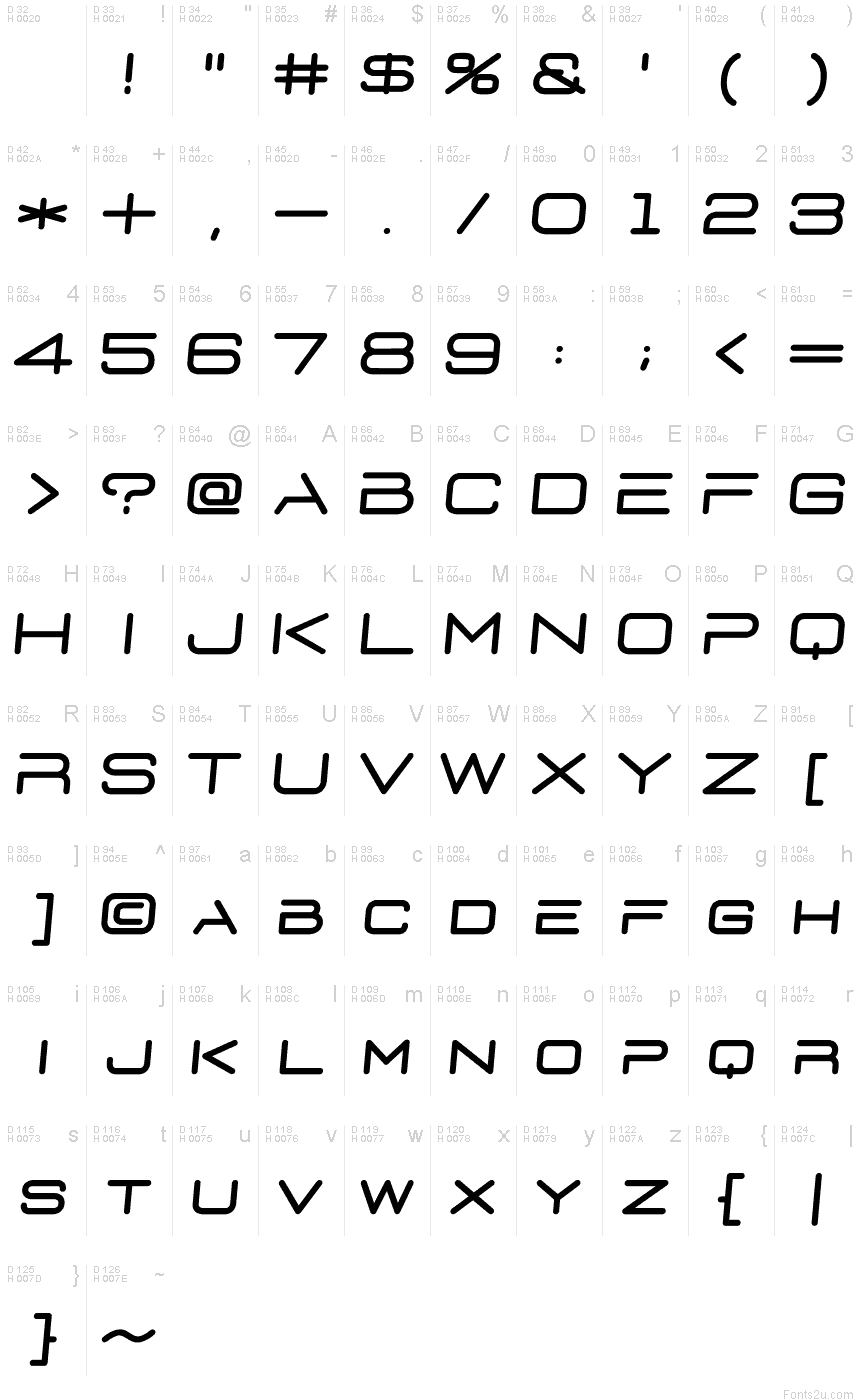
D3 Euronism italic
Krój D3 Euronism italic od DigitalDreamDesign łączy w sobie elegancki klimat science-fiction z łagodnymi, zaokrąglonymi kształtami i pewnym pochyleniem w prawo. Szerokie litery, równomierna grubość linii i kwadratowe krzywe tworzą dynamiczny, techniczny rytm, który pozostaje czytelny nawet w mniejszych nagłówkach. To darmowy font, który natychmiast kojarzy się z technologią, ruchem i nowoczesnym sprzętem.
Ten darmowy font świetnie sprawdza się w interfejsach gier, logotypach esportowych, identyfikacji wizualnej marek technologicznych, plakatach sci-fi oraz wyrazistych tytułach wydarzeń. D3 Euronism italic dodaje okładkom albumów czy miniaturom na YouTube powiewu szybkości i cyfrowego stylu, nie sprawiając wrażenia bałaganu. Wypróbuj go w dużym rozmiarze z szerokim kerningiem i zestaw z prostym, geometrycznym bezszeryfowcem w tekście głównym, aby zachować przejrzysty i konkretny wygląd projektu.
Charakter wzoruNachylony